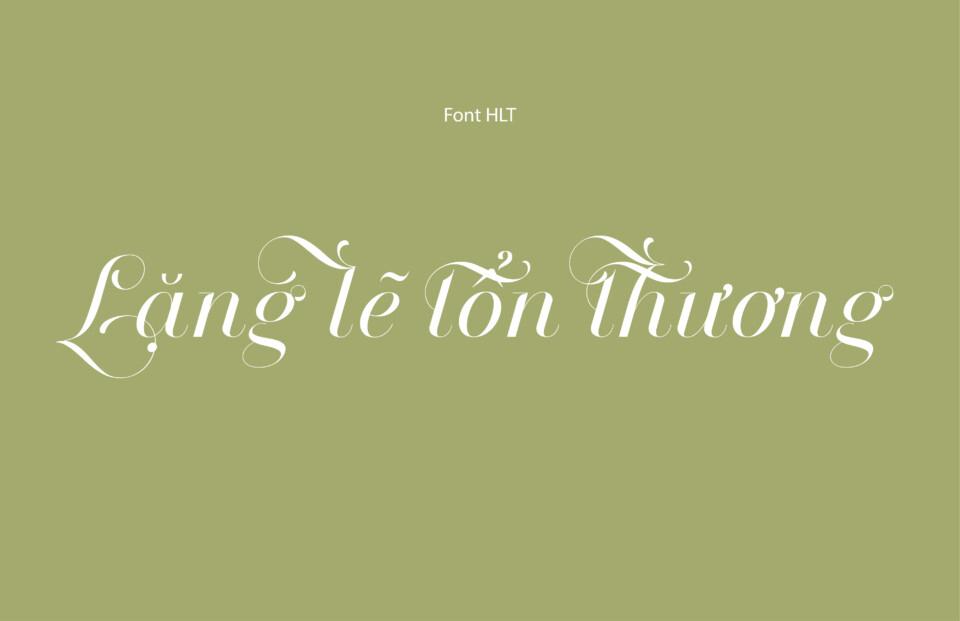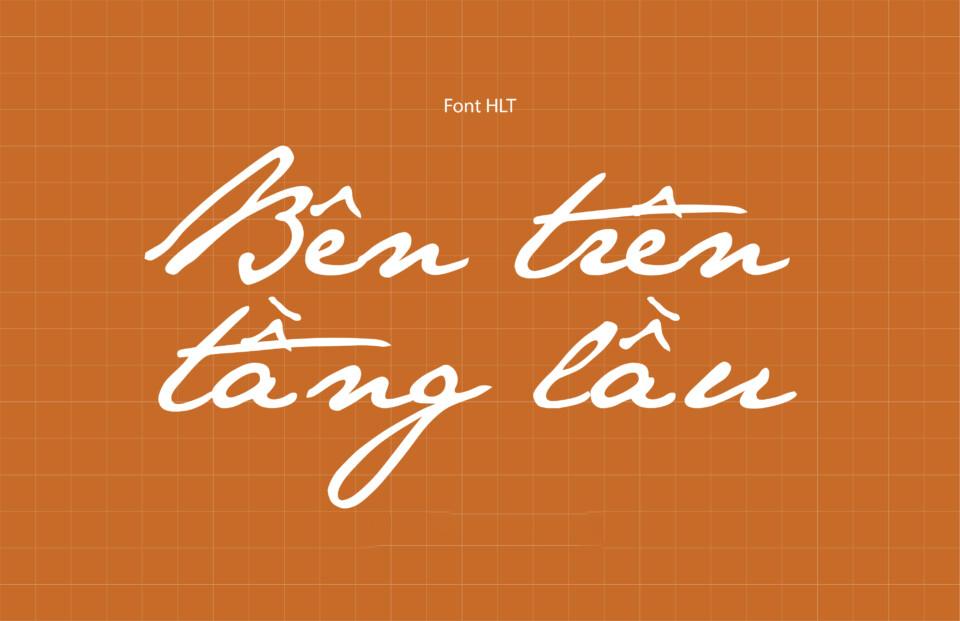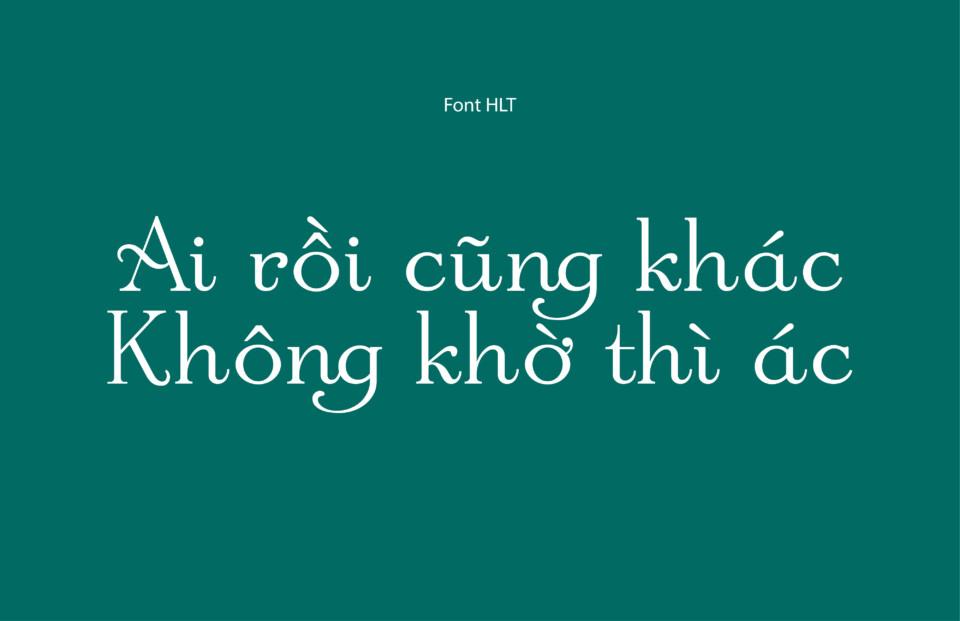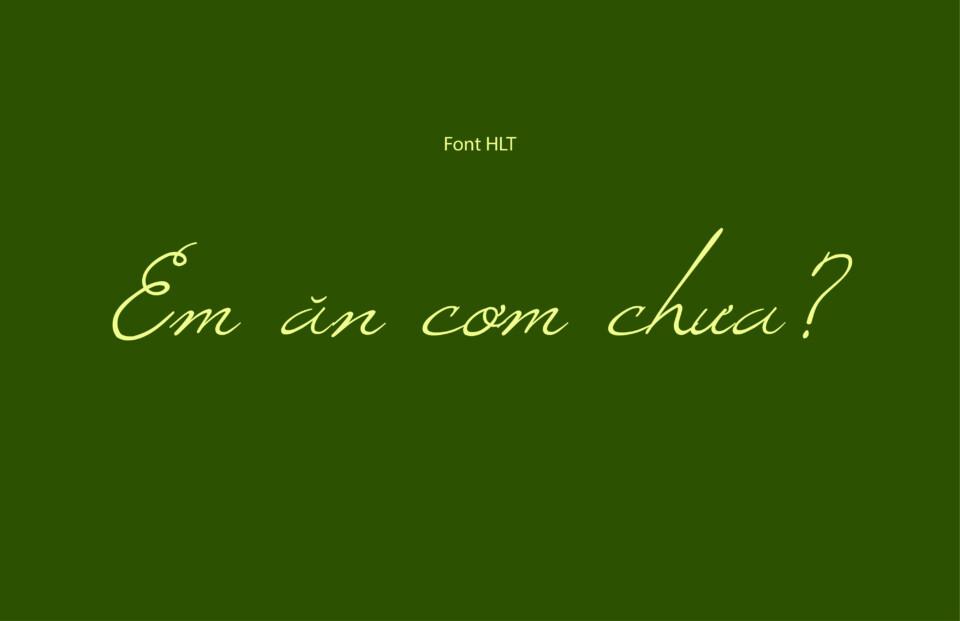
Font HLT Việt hóa là bộ sưu tập các phông chữ đồ họa mang đậm phong cách cổ điển, hoài niệm và giàu tính nghệ thuật, được gắn liền với tên tuổi của nhà thiết kế Hùng Lân trong làng Typography Việt Nam. Với cấu trúc đường nét phóng khoáng, đậm chất bảng hiệu vẽ tay truyền thống và các tiêu đề báo chí thế kỷ trước, bộ font này là lựa chọn số một cho các dự án thiết kế bao bì đặc sản, quán cà phê phong cách Retro và các ấn phẩm văn hóa dân tộc. Doozypack.vn cung cấp link download font Việt hóa HLT trọn bộ chuẩn kỹ thuật, giúp bạn sở hữu kho phông chữ hoài cổ độc đáo mà không lo gặp bất kỳ lỗi hiển thị dấu thanh nào khi thiết kế in ấn.
Bộ font HLT Việt hóa là gì? Dấu ấn Typography hoài cổ độc đáo
Hệ thống font HLT đã đồng hành cùng nhiều thế hệ người làm đồ họa tại Việt Nam, trở thành biểu tượng cho phong cách thiết kế mang đậm hơi thở bản địa.
Nguồn gốc và tinh thần đồ họa truyền thống
Đặc trưng lớn nhất của Font HLT Việt hóa là sự mô phỏng sống động ngôn ngữ thị giác của những thập niên 80 – 90. Các con chữ sở hữu hình khối chắc chắn, dứt khoát nhưng luôn có những nét cách điệu ngẫu hứng ở phần chân hoặc các góc bo. Phong cách này mang lại sự mộc mạc, gần gũi và gợi nhớ sâu sắc về không gian văn hóa Việt Nam thời kỳ đổi mới, giúp ấn phẩm của bạn toát lên chất nghệ nhân và giá trị truyền thống bền vững.
Kỹ thuật tạo dấu tiếng Việt chỉn chu và cân đối
Nỗi lo lắng thường gặp của designer khi tìm kiếm font hoài cổ là hệ thống dấu thanh bị thô hoặc nhảy lỗi ký tự lạ. Bộ font HLT Việt hóa giải quyết triệt để vấn đề này nhờ quy chuẩn vẽ dấu bám sát ngữ pháp và thói quen thị giác của người Việt. Các dấu sắc, huyền, hỏi, ngã, nặng được căn chỉnh tỉ mỉ về độ nghiêng và khoảng cách, đảm bảo dòng chữ tiêu đề trên bao bì luôn cân đối, đẹp mắt và dễ đọc từ khoảng cách xa.
Các phong cách nổi bật trong bộ sưu tập font HLT
Khi bạn thực hiện tải font HLT Việt hóa, bạn sẽ tiếp cận được nhiều phân nhánh thẩm mỹ đa dạng để phục vụ từng ý tưởng thiết kế cụ thể:
- Nhóm HLT Bảng hiệu (Signboard Display): Nét chữ dày bản, hình khối vuông vức và vững chãi, lý tưởng để làm tiêu đề chính trên nắp hộp quà Tết, bảng hiệu hoặc túi giấy thời trang Retro.
- Nhóm HLT Nét cọ (Brush Script): Những đường nét chuyển động tự do, mô phỏng nhát bút lông đẫm mực, phù hợp cho nhãn chai rượu, trà cổ thụ hoặc bao bì bánh kẹo dân dã.
- Nhóm HLT Cổ điển có chân (Vintage Serif): Nét thanh đậm rõ ràng mang phong cách báo chí xưa, thích hợp cho việc trình bày nội dung câu chuyện thương hiệu hoặc thông tin sản phẩm cao cấp.
Tại sao designer nên tải font Việt hóa HLT cho thiết kế bao bì?
Trong ngành thiết kế và sản xuất bao bì tại Doozypack.vn, HLT luôn là sự lựa chọn ưu tiên cho các dự án mang đậm hồn Việt:
- Khẳng định giá trị văn hóa và nguồn gốc: Một chiếc hộp giấy đựng trà hay cà phê sử dụng font HLT sẽ lập tức tạo dựng được niềm tin về sự nguyên bản, chất lượng gia truyền và sự tâm huyết của nhà sản xuất.
- Tạo điểm nhấn thị giác khác biệt: Giữa hàng loạt mẫu bao bì hiện đại sử dụng phông chữ không chân công nghiệp, nét thô mộc của font HLT giúp sản phẩm nổi bật hoàn toàn trên kệ hàng.
| Nhóm Font | Đặc điểm thị giác | Ứng dụng đề xuất tại Doozypack.vn |
| HLT Signboard | Nét dày, vuông vức, vững chãi | Tiêu đề chính hộp quà Tết, bảng hiệu quán cà phê Retro. |
| HLT Serif Vintage | Có chân cổ điển, trang trọng | Nội dung câu chuyện thương hiệu trên vỏ hộp trà, bánh mứt. |
| HLT Decorative | Phá cách, uốn lượn nghệ thuật | Dùng cho tem nhãn chai rượu, bao lì xì, thiệp mời sự kiện. |
03 Ứng dụng thực tế của font HLT trong sản xuất bao bì tại Doozypack.vn
Nét đẹp mộc mạc của font HLT mang lại hiệu ứng thị giác đắt giá trên các dòng sản phẩm bao bì thực tế do Doozypack.vn sản xuất:
- Bao bì Cà phê hạt & Trà đặc sản: Nét chữ hoài cổ kết hợp hoàn hảo cùng chất liệu giấy Kraft nâu thô mộc, tạo nên phong cách cổ điển, nguyên bản và đậm đà phong vị truyền thống.
- Hộp bánh Trung thu & Quà Tết: Tiêu đề in bằng font HLT kết hợp kỹ thuật ép kim nhũ vàng trên nền giấy đỏ mang lại không khí lễ hội rực rỡ và trang trọng.
- Túi giấy thời trang Vintage: Tên cửa hàng in bằng font HLT trên túi giấy Ivory cán màng mờ tạo phong cách hoài niệm, tinh tế và ghi dấu ấn sâu đậm trong lòng khách hàng.